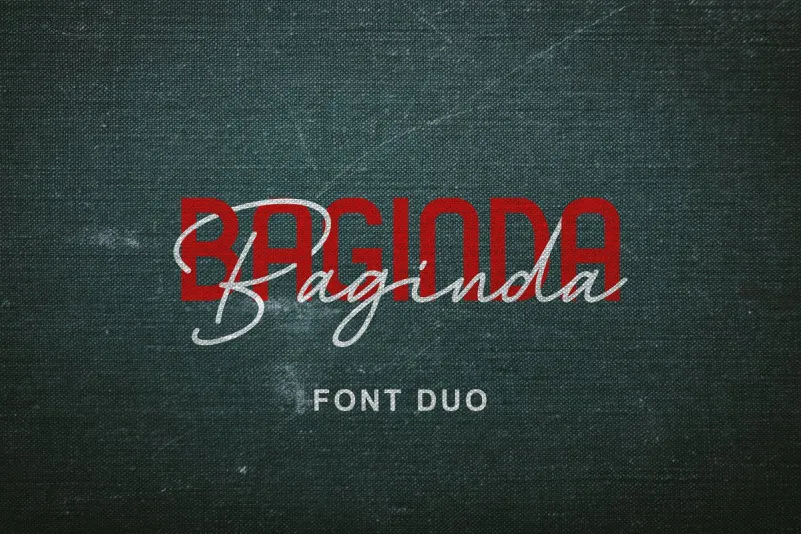
Baginda Font Duo
Olá! Estamos muito felizes em apresentar a vocês Baginda Font Duo, uma combinação interessante de duas fórmulas: um tipo tipográfico e outro de sans-serif. Este duo foi projetado por M.0Type, designer brasileiro que trouxe para nós algo único e luxuoso. Introduzimos o Baginda Script Font Demo, obra prima da designer zuzulgo, que apresenta uma estética elegante e sofisticada. Este tipo de texto não apenas é perfeito para fins comerciais como também combina perfeitamente com criações de marca, logomarcas, capas de revistas e até cartões de casamento. A Baginda Font Duo traz dois estilos distintos: o regular e o oblique, com cada um oferecendo uma experiência única. O tipo tipográfico é concebido para imitar a aparência natural da escrita manual, mantendo seu charme elegante e aparentemente confuso mas, ao mesmo tempo, exibindo uma personalidade única. Estas fórmulas são perfeitamente adaptadas para diversos usos gráficos, desde o design de logotipos até os maiores projetos de publicidade. A Baginda Font Duo é um tesouro para qualquer designer ou marca que busca incorporar estilo e elegância em seus trabalhos.